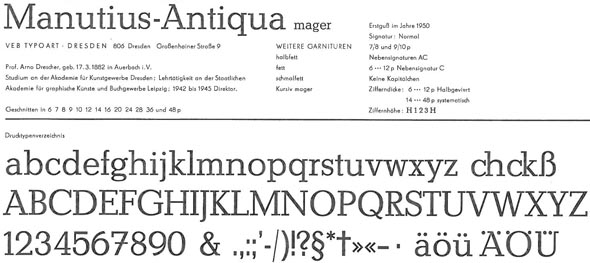
typische "DDR-Ausweisschrift" mit welcher ttf nachahmen?
Abgesehen davon, daß es »die« Ausweisschrift der DDR nicht gegeben haben wird: Das Bild ist zu klein, um die verwendete Schrift vernünftig erkennen zu können.
Hier nun eine größere Fassung:
Hoffentlich hilft das ein wenig beim Erkennungsvorgang...
@Joshua K.: Wow! Ich habe jetzt mal eine Candida "danebengehalten". Sie sieht wirklich beinahe identisch aus. Respekt und nochmals Danke!
Lese ich da wirklich Amatuer statt Amateur?
Da hat sich halt jemand auf die Armatur der Setzmaschine gesetzt. ;-)
Trennungen wie »Spieler-laubnis« sind ja auch nicht gerade die Hohe Schule der Schriftsetzerei.
Für den Ausweis wurde übrigens die Manutius von Drescher verwendet:
@Pachulke: historisch wäre das dann ja geklärt. Gäbe es aus deiner Sicht eine vergleichbare TTF?
… Gäbe es aus deiner Sicht eine vergleichbare TTF?
Wie Joshua schon angemerkt hat, dürfte die Candida am nächsten dran sein.
Die Baltica von ParaType geht auch in die Richtung …
Ich glaub übrigens nicht, dass die angefragte Spielerlaubnis ein von der Wertpapierdruckerei gemachter DDR-weiter offizieller Ausweis war, sondern wahrscheinlicher ist, dass diese Spielerlaubnis nur in einer bestimmten Zeit in einer bestimmten Gegend (vermutlich Bezirk) und (sogar möglicherweise nur innerhalb bestimmter Kreise gültig war) so aussah, weil die zufällig damit beauftragte Druckerei halt grade die Manutius hatte. Woanders sahen diese "Ausweise" anders aus, weil woanders gedruckt. Wie halt heutzutage auch jeder Verein oder Fitnessladen oder wer auch immer sich seine Ausweise amateurmäßig zusammenschraubt. Zu DDR-Zeiten genügte allein die Tatsache, dass eine Druckschrift verwendet wurde (und die Manutius gab es meines Wissen nur in Blei) zur allgemeinen Fälschungssicherheit - Druckschriften gabs eben nur in (mehr oder weniger kontrollierten, immer aber kontrollierbaren) Druckereien. Qualitativ halbwegs gute Kopiermöglichkeiten gabs damals eben noch nicht ... Und so war jede gedruckte Schrift quasi amtlich ...
Und demzufolge gab es praktisch alle Schriften, die in Druckereien vorhanden waren und sich halbwegs dafür eigneten auch in "Ausweisen". Die Manutius und die Technotyp als Serifenbetonte wirkten immer besonders amtlich und wurden deshalb dafür besonders gern genommen, ich hab aber auch schon "Ausweise" unter Verwendung von Thomas-Versalien, Erler-Versalien (eigentlich die klassische Urkundenschriften), der Post-Antiqua (klassische Trauerkartenschrift) und Schreibschriften wie Kurier, Agitator, Splendor etc. gesehen. Selbst gebrochene wurden manchmal verwendet ...
der zu seinen Gigs damals als Schallplattenunterhalter gleich mit selbstgedruckten (!) Fahrkarten gefahren ist ... und natürlich auch bei der 60/40 Regel wurde weitergeschummelt ... es war eben nicht alles schlecht ...
Aber trotzdem: ich halte die Manutius immer noch für eine grausame Schrift und die Technotyp finde ich sogar noch schlimmer ...
Und wollte mit der letzten Bemerkung nicht sagen, daß der vorgezeigte Ausweis eine illegale Arbeit war, sondern sicherlich hochoffiziell in Auftrag gegeben wurde, aber vermutlich im Bezirk Gera anders aussah als in Rostock ... weil halt ein anderer kleiner Ausweisdrucker am Werk war. Es sieht zumindest nicht so aus, als käme der aus der Wertpapierdruckerei Leipzig oder vom "Vordruckleitverlag" (jaja, sowas gab es wirklich!).
Und über weitere Beispiele für grausame selbstgemachte "Ausweise" würde ich mich trotzdem freuen ...
… ich hab aber auch schon "Ausweise" unter Verwendung von … Splendor etc. gesehen.
Splendor für einen Ausweis? Das würde ich ja gern mal sehen. :-o
Es sieht zumindest nicht so aus, als käme der … vom "Vordruckleitverlag" ...
Die VLV-Drucksachen sahen nicht unbedingt aufwendiger aus. Wenn Holger so freundlich ist, uns einen ordentlichen Scan der Rückseite einzustellen, kann man über die Druckgenehmigungsnummer vielleicht etwas herausfinden.